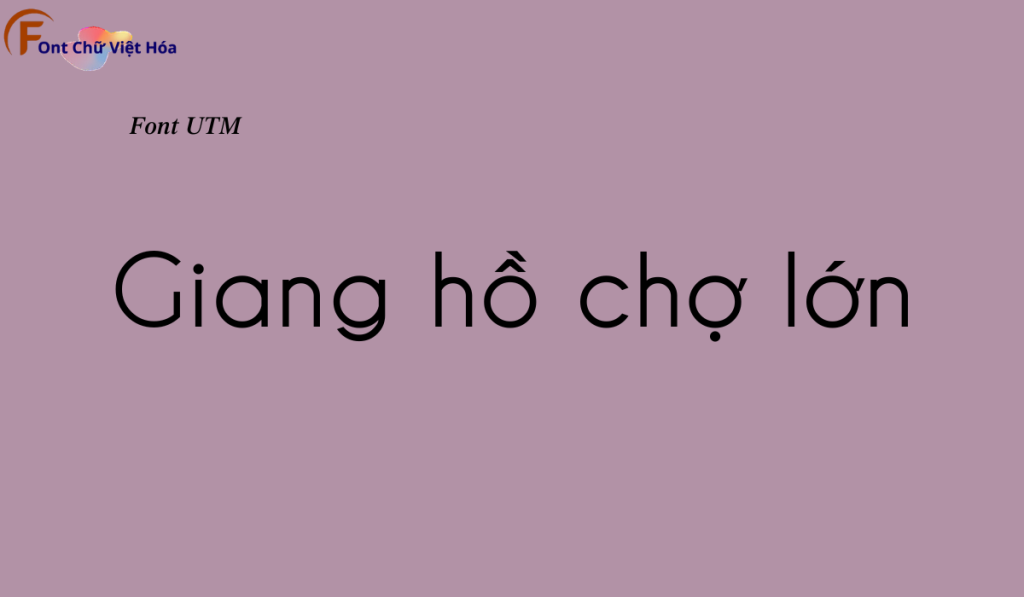
Font UTM Caviar Việt Hóa
Font UTM Caviar Việt Hóa là một font chữ không chân thanh mảnh, thuộc bộ font UTM. Được thiết kế với mục tiêu mang lại sự tinh tế và hiện đại, font này lý tưởng cho các dự án thiết kế như thiệp mời, bìa sách, và các sản phẩm thủ công. Với các nét chữ thanh mảnh và độ dày đều đặn, Font UTM Caviar Việt Hóa không chỉ dễ đọc mà còn tạo cảm giác thanh lịch và sáng tạo. Việc Việt hóa font giúp người dùng dễ dàng tích hợp vào các thiết kế tiếng Việt, mang lại sự tiện lợi và nâng cao tính thẩm mỹ.